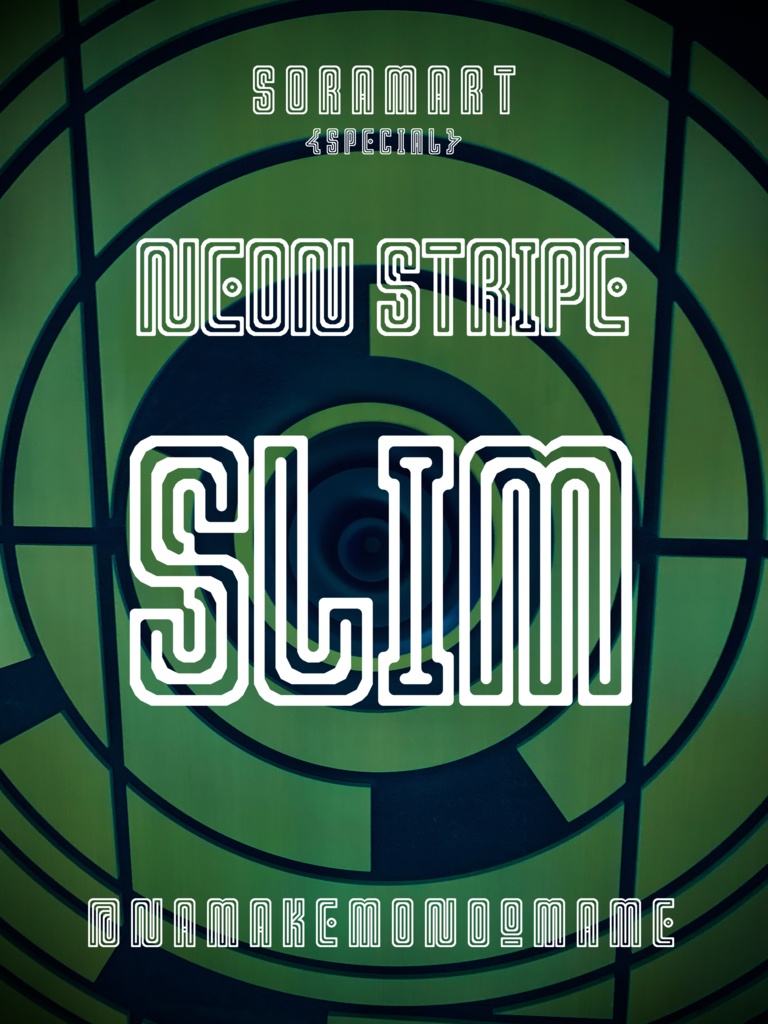
そらマートフォントデータ”Neon Stripe Slim”ダウンロード商品¥ 0無料ダウンロードNeon_Stripe_Slim.zip (4.7 MB)Neon_Stripe_Slim.zip「ギフトとして贈る」とはネオンサインをイメージした細長フォント "Neon Stripe Slim" です。 「TrueTypeフォントファイル」という形式です。 ダウンロードした後、Zipファイル内のデータをインストールしてお使いください。 このフォントは商用利用可となっております。 お客様の制作・創作活動のお役に立てれば幸いです。 ※使用上の注意事項などは、添付のReadmeをお読みください。 ※このフォントは当店の商品を”BOOST”いただいた返礼品です。2週間限定で無料配布しますので、よろしくお願いします。そらマートFANBOX開設中フォント・書体フォントデータ”Packing Sans Serif Unbalanced”そらマート¥ 0フォント・書体フォントデータ”Rolling Cute”そらマート¥ 0フォント・書体フォントデータ”Tricky Wire Merge”そらマート¥ 2,500フォント・書体フォントデータ”Tricky Layer Wide”そらマート¥ 0フォント・書体フォントデータ”Tricky Layer”そらマート¥ 0フォント・書体フォントデータ”Popcorn Tab Plasma”そらマート¥ 2,500フォント・書体フォントデータ”Popcorn Tab Heavy”そらマート¥ 2,500フォント・書体フォントデータ”Popcorn Tab”そらマート¥ 2,500フォント・書体フォントデータ”Tetra Pixel Dash”そらマート¥ 2,500フォント・書体フォントデータ”Tetra Pixel Fluid”そらマート¥ 2,500フォント・書体フォントデータ”Tetra Pixel”そらマート¥ 2,500フォント・書体フォントデータ”Neon-Lit Empire Long”そらマート¥ 2,500フォント・書体フォントデータ”Neon-Lit Empire”そらマート¥ 2,500フォント・書体フォントデータ”Jumping Meteor Drop”そらマート¥ 2,500フォント・書体フォントデータ”Jumping Meteor Wide”そらマート¥ 2,500フォント・書体フォントデータ”Jumping Meteor”そらマート¥ 2,500フォント・書体フォントデータ”Ragtime Key Tall”そらマート¥ 2,500フォント・書体フォントデータ”Ragtime Key Bold”そらマート¥ 2,500フォント・書体フォントデータ”Ragtime Key”そらマート¥ 2,500フォント・書体フォントデータ”Cocoon Bullet Emerge”そらマート¥ 2,500もっと見る